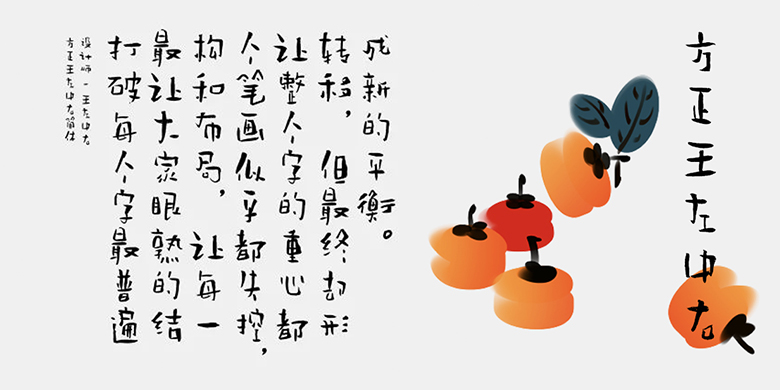
方正王左中右体和繁体
写字大致有两个方向,一个是追求局部笔画的笔锋和形状,一个是追求整体汉字的结构和布局。方正王左中右体追求的是后者。具体而言,就是打破每个字最普遍最让大家眼熟的结构和布局,放大不该放大的,缩小不该缩小的,拉长不该拉长的,拓宽不该拓宽的,不该空的地方空,不该破的地方破,让每一个笔画似乎都失控,让整个字的重心都转移,但最终却形成新的平衡。字还是那个字,只是增减挂钩了。创作过程与其说是在写字,不如说是在画画,在拼图,把“老字”的笔画一个个拆散,变形,再重新拼成一个歪瓜裂枣的“新字”。如果用形容词描述这个字体的话,可能下面三个字可能会比较接近:拙,顽,懒。